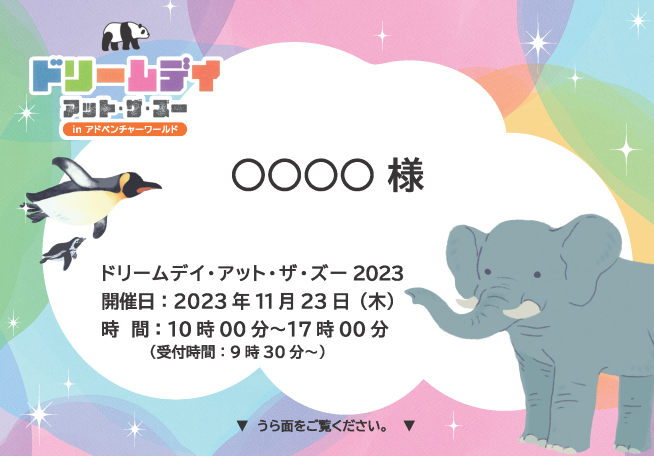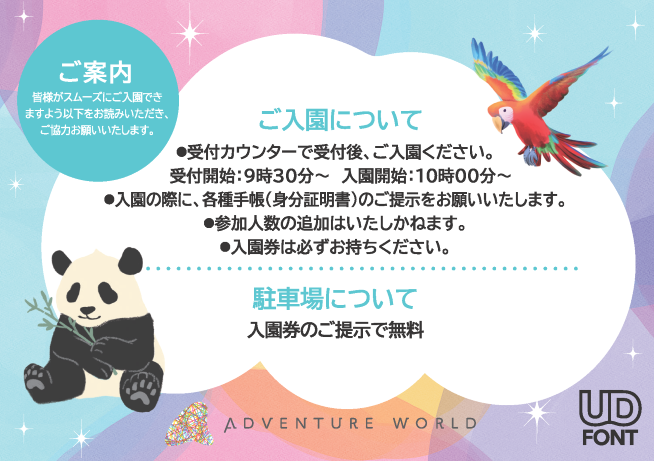
モリサワ 「ドリームデイ・アット・ザ・ズー 2023 in アドベンチャーワールド」に協賛
株式会社モリサワは「持続可能な開発目標(SDGs:Sustainable Development Goals)」の取り組みの一環として、和歌山県のアドベンチャーワールドで開催される「ドリームデイ・アット・ザ・ズー 2023 in アドベンチャーワールド」(主催:和歌山ドリデイ2023実行委員会)に協賛します。
アドベンチャーワールドでは、2017年より営業終了後にパークを貸し切り、障害のあるお子さまとその家族を無料で招待する「ドリームナイト・アット・ザ・ズー」を開催。2021年より一生思い出に残るそんな1日をよりたくさん楽しんでいただきたいという想いから、パークを1日貸し切り「ドリームデイ・アット・ザ・ズー」と名称を変更し開催しています。2023年も全国から募集を募り、1,000組(4,000名)のご家族を無料で招待します。
モリサワは、本イベント主催の和歌山ドリデイ2023実行委員会が目指す「特性や属性に関わらず一人一人が社会の構成員として、ともに助け合って生きていける社会、“障害”が障害でなくなる社会の実現」に賛同し、協賛パートナーとして参画します。
「UDフォント」による見やすさ、読みやすさへの配慮
障害のあるお子さまとそのご家族の特別な1日のため、各種ガイドや掲示物には視覚に障害のある方にも見やすく、読みやすくなるようモリサワが提供する「UDフォント」(BIZ UDゴシック)が使用されます。
【UDフォントが使用される制作物例】
・イベント当日のパークガイド(パークマップや各アトラクションの時間、場所などが記載されたガイド)
・イベント当日のエンジョイガイド(遊技機種の対象年齢や料金などが記載されたガイド)
・イベント当日のパーク内掲示物(イベントブースやパネルなど)
・ドリームデイ・アット・ザ・ズー2023への招待状(当選された方に送付)
・企業協賛案内チラシ(本イベントの協賛企業を紹介)
開催概要
ドリームナイト・アット・ザ・ズーとは
1996年にオランダのロッテルダム動物園で発足した活動から始まり、障害のあるお子さまたちとそのご家族を動物園・水族館に招待する取り組み。現在は日本を含め世界中で実施されている。
※和歌山ドリデイ2023実行委員会は、2021年より家族で目一杯楽しんでいただけるようパークを1日貸し切る日中開催に変更し、名称をドリームデイ・アット・ザ・ズーとしました。
和歌山ドリデイ2023実行委員会について
2017年より前身となる「ドリームナイト・アット・ザ・ズー」をアドベンチャーワールド(運営:株式会社アワーズ)主催で開催。2021年に白浜町をはじめイベント主旨に賛同した全国のパートナーによって「和歌山ドリデイ実行委員会」を立ち上げ、「“特別なとき” が“当たりまえのとき” に変わり、特性や属性に関わらず一人一人が社会の一員として、ともに助け合って生きていける社会」の実現を目指して活動しています。 また、ご支援くださるみなさまと共に「ドリームデイ・アット・ザ・ズー」を継続的に行い、応援の輪を広げるクラウドファンディングにも挑戦しています。